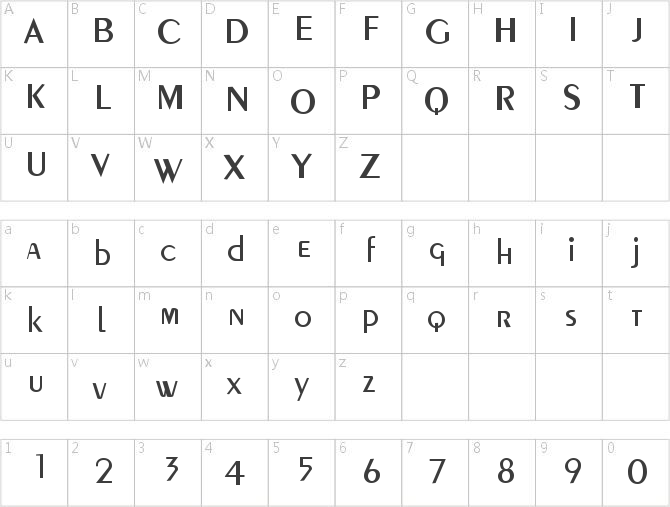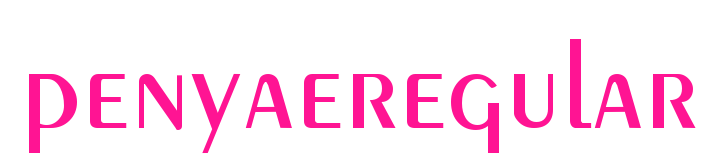
penyaeregular
penyaeregular介紹
penyaeregular字體字庫(kù)是一款讓人賞心悅目、百看不厭的英文字體,適合各類(lèi)廣告和產(chǎn)品包裝設(shè)計(jì)應(yīng)用,字體大小0.03MB,格式為ttf字體,上傳用戶(hù)是得·岸,作者/版權(quán)方為未知